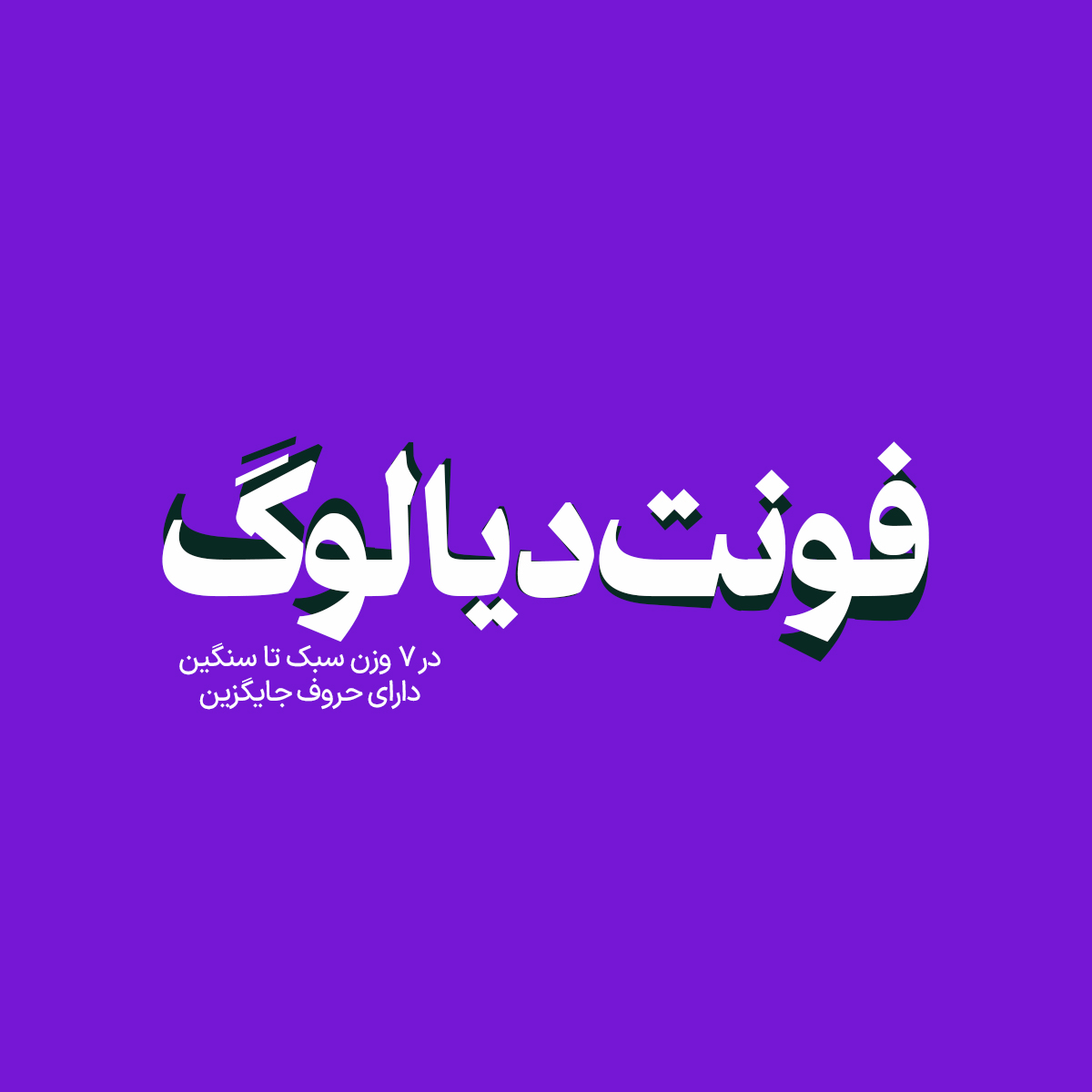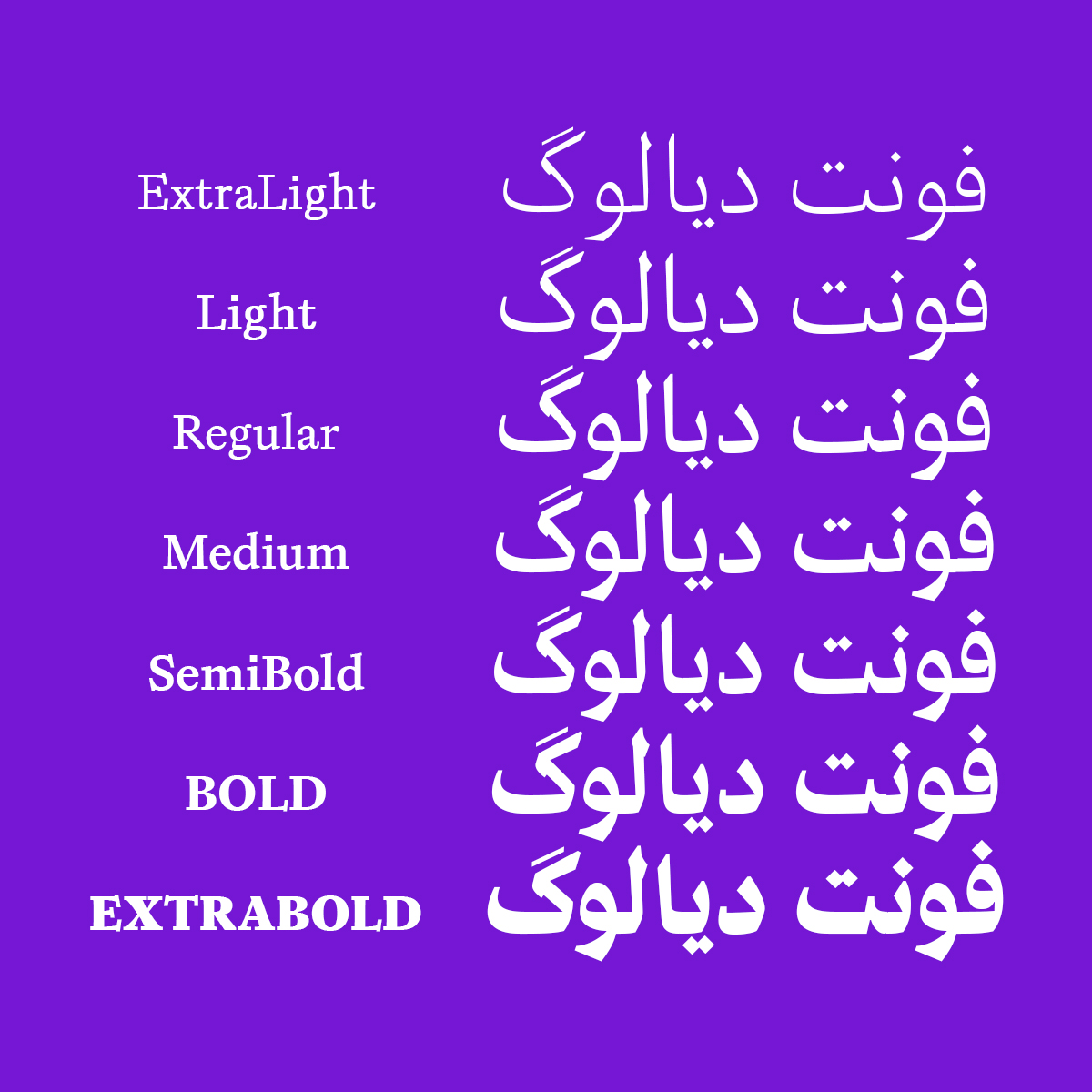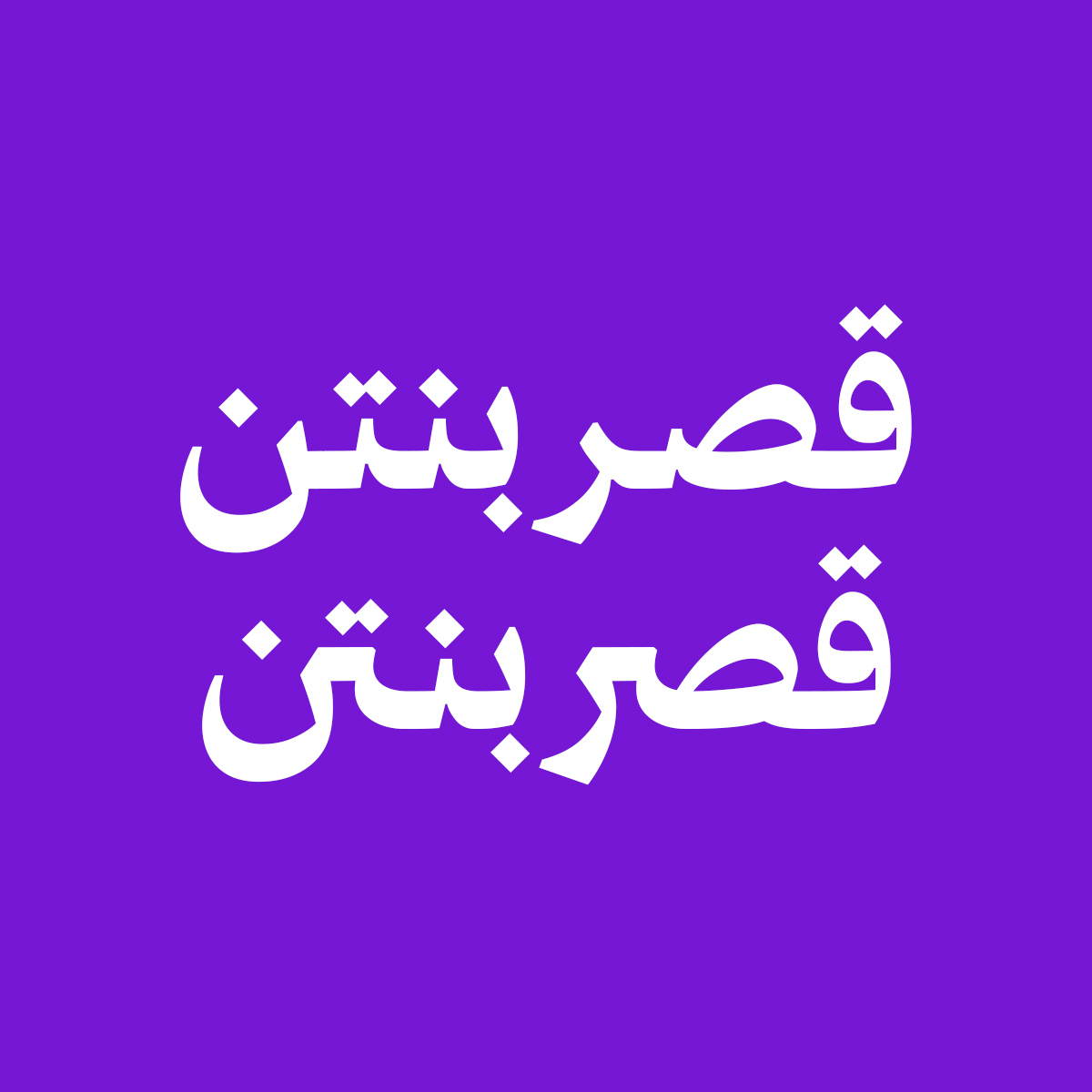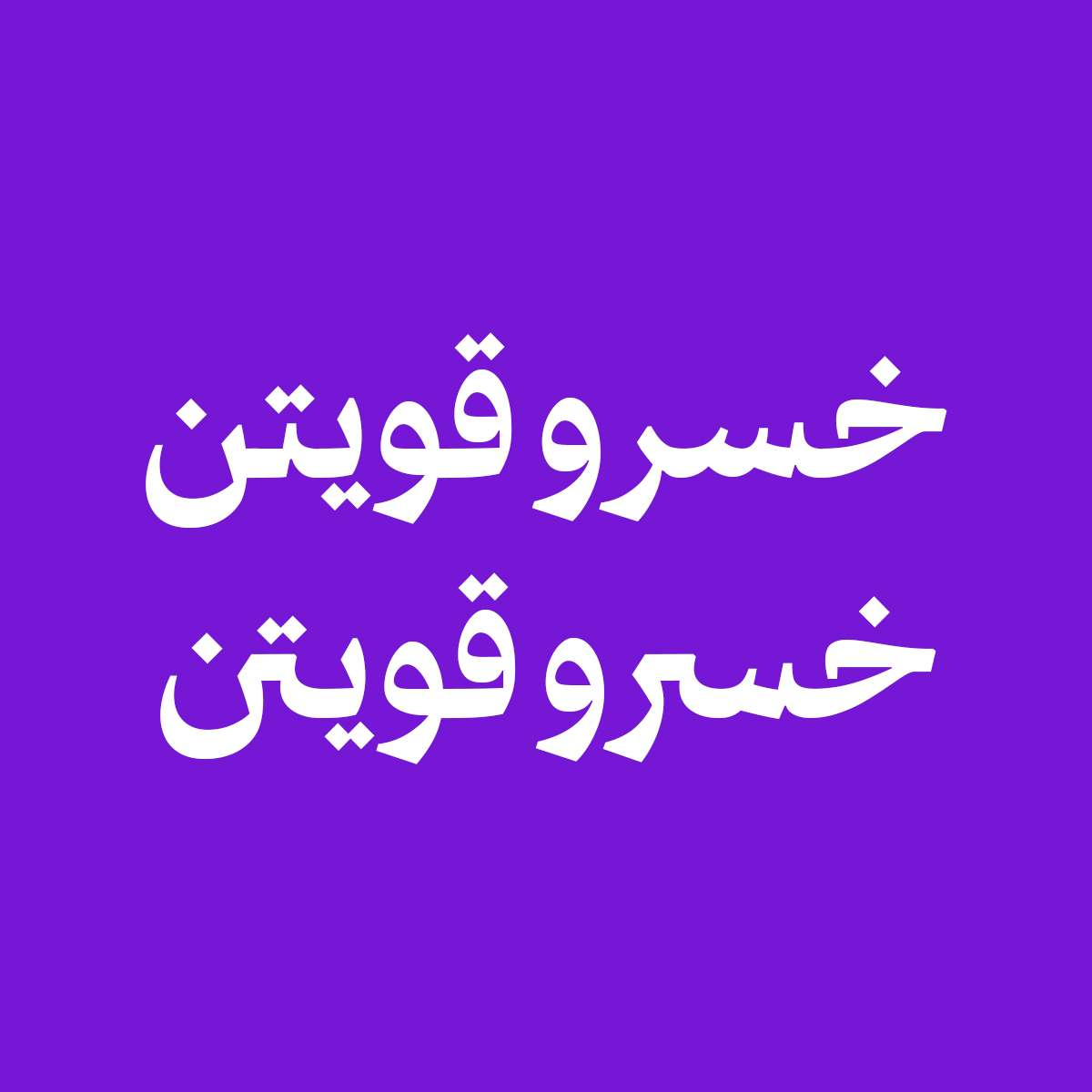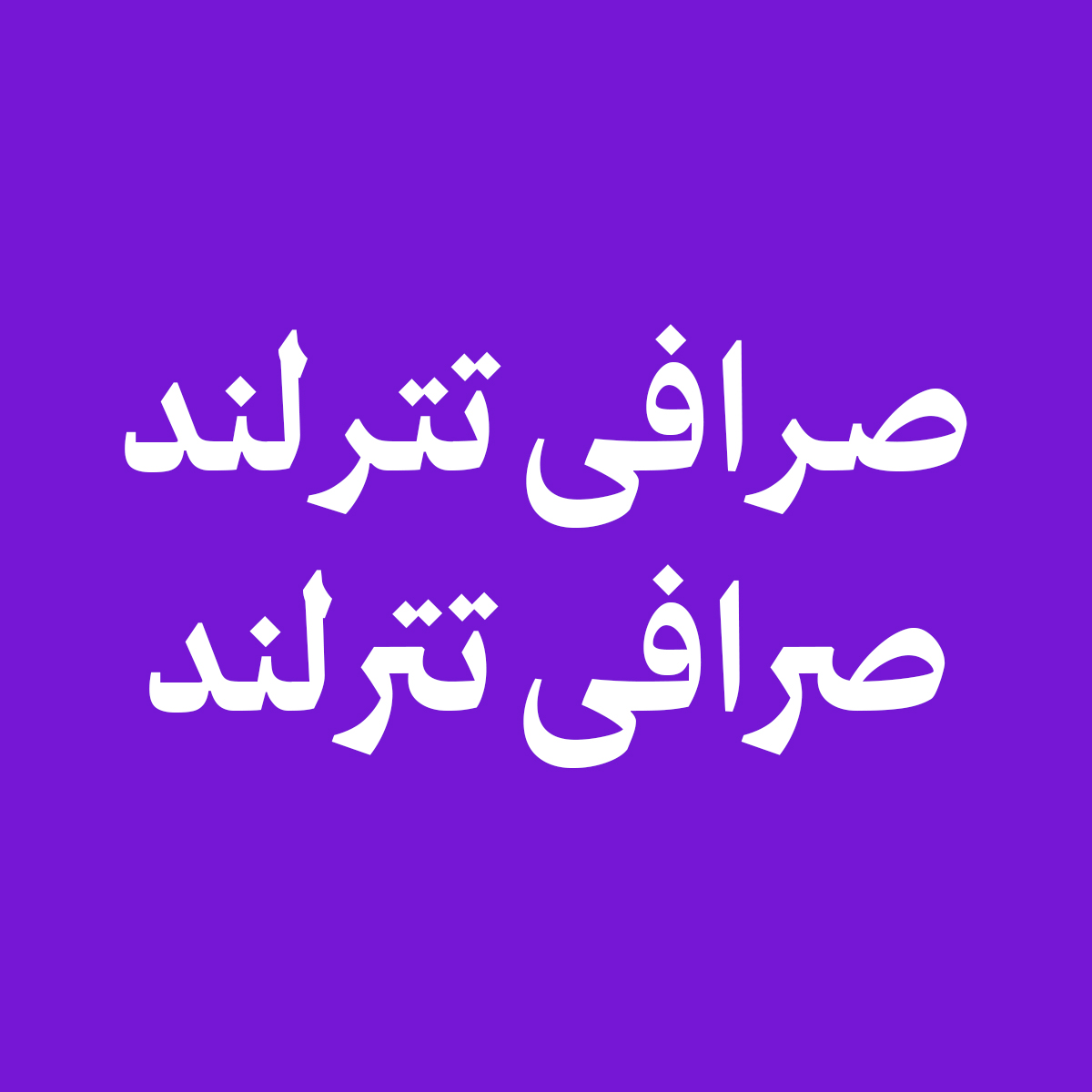
فونت فارسی دیالوگ Dialogue Font
فونت فارسی دیالوگ یک فونت فارسی خاص می باشد که به طراحان گرافیک امکان خلق طرح های زیبا و حرفه ای به سادگی یک تایپ میدهد.فونت دیالوگ شامل 7 وزن و دارای حروف جایگزین است که این خانواده فونت را زیبا، دوستانه، مدرن و خوانا میکند. فونت دیالوگ برای متنهای طولانی، اندازههای کوچک و صفحه نمایش بهینه شده است تا خوانایی در ابعاد کوچک را در هر شرایط استفاده به ویژه برای فضای وب و صفحات دیجیتال واضحتر کند.